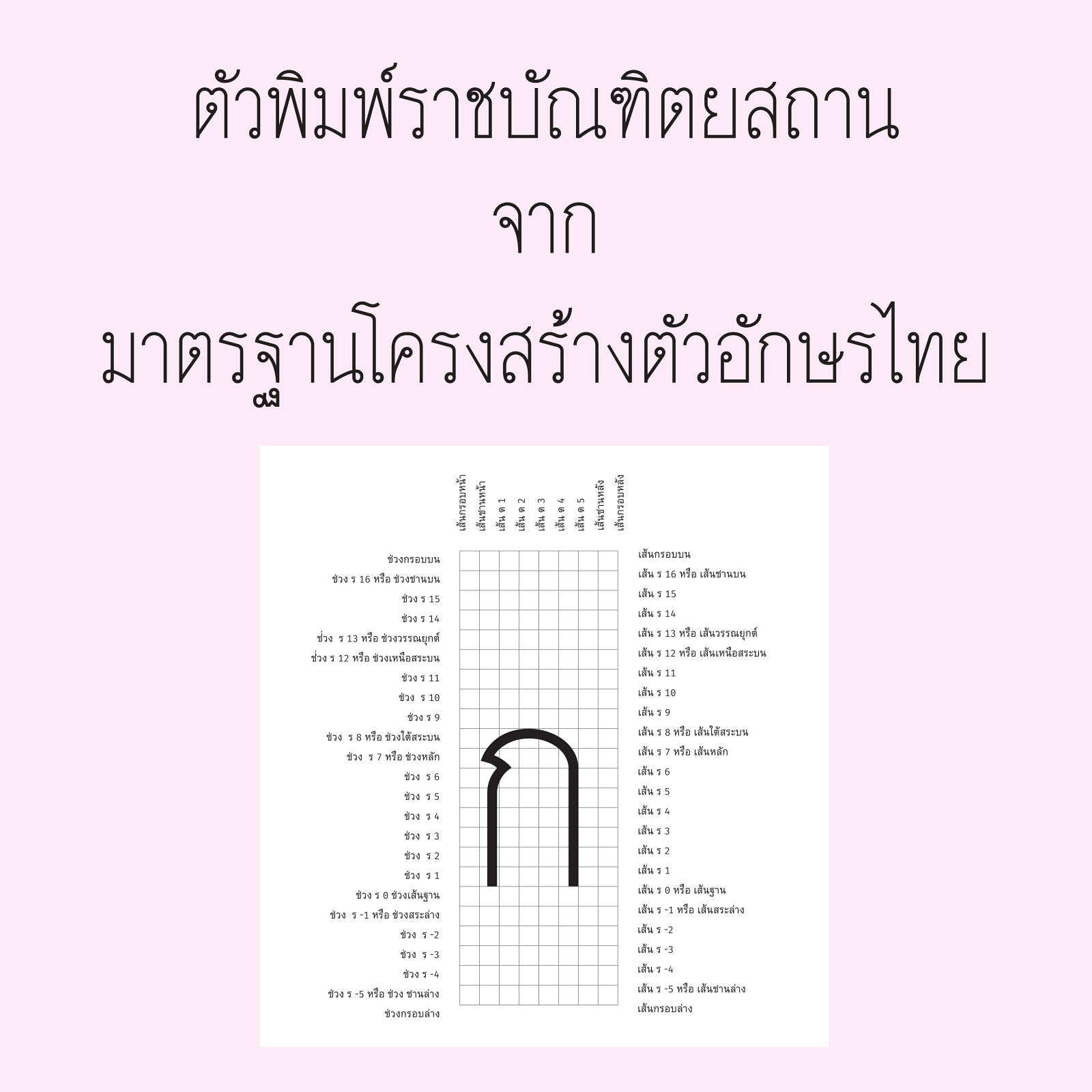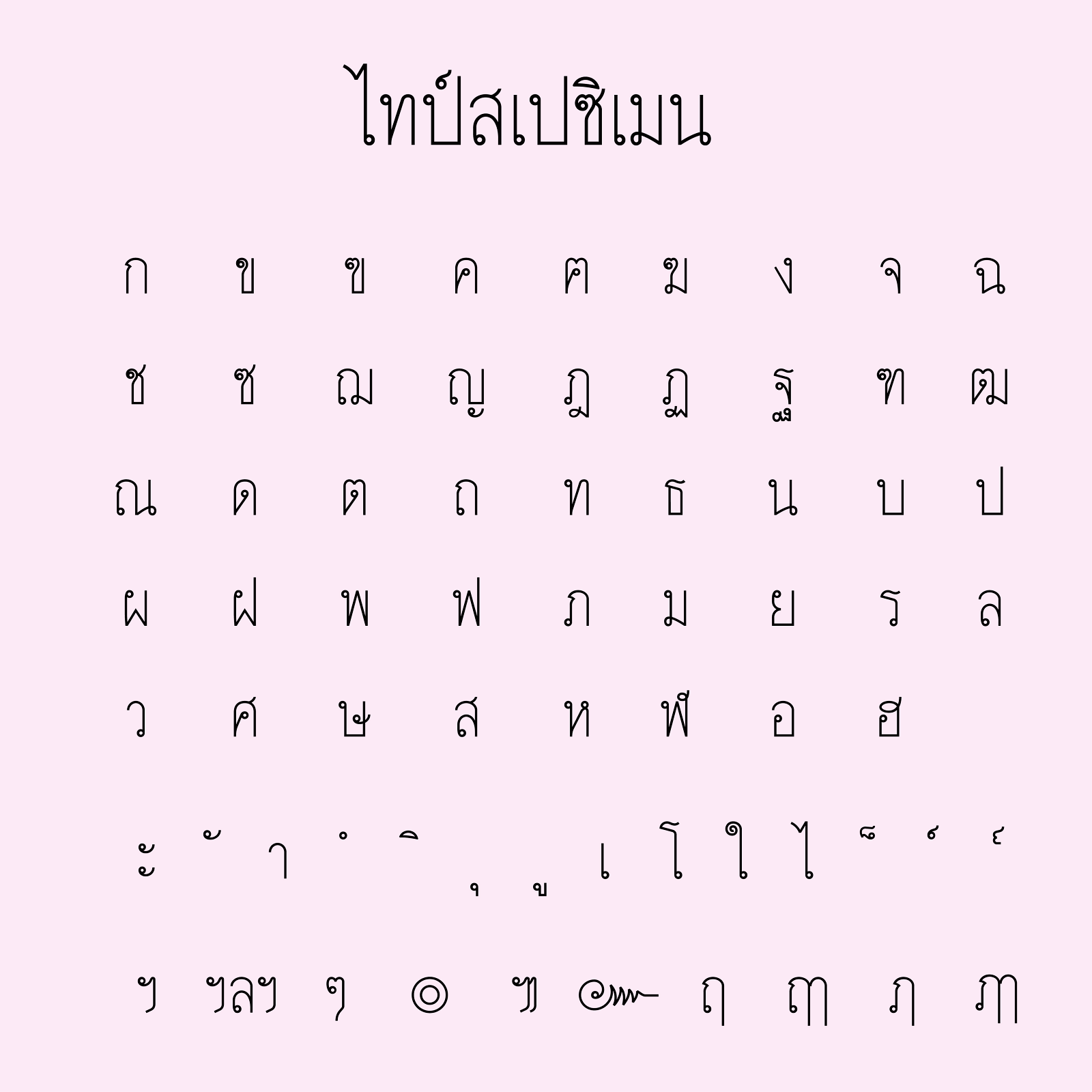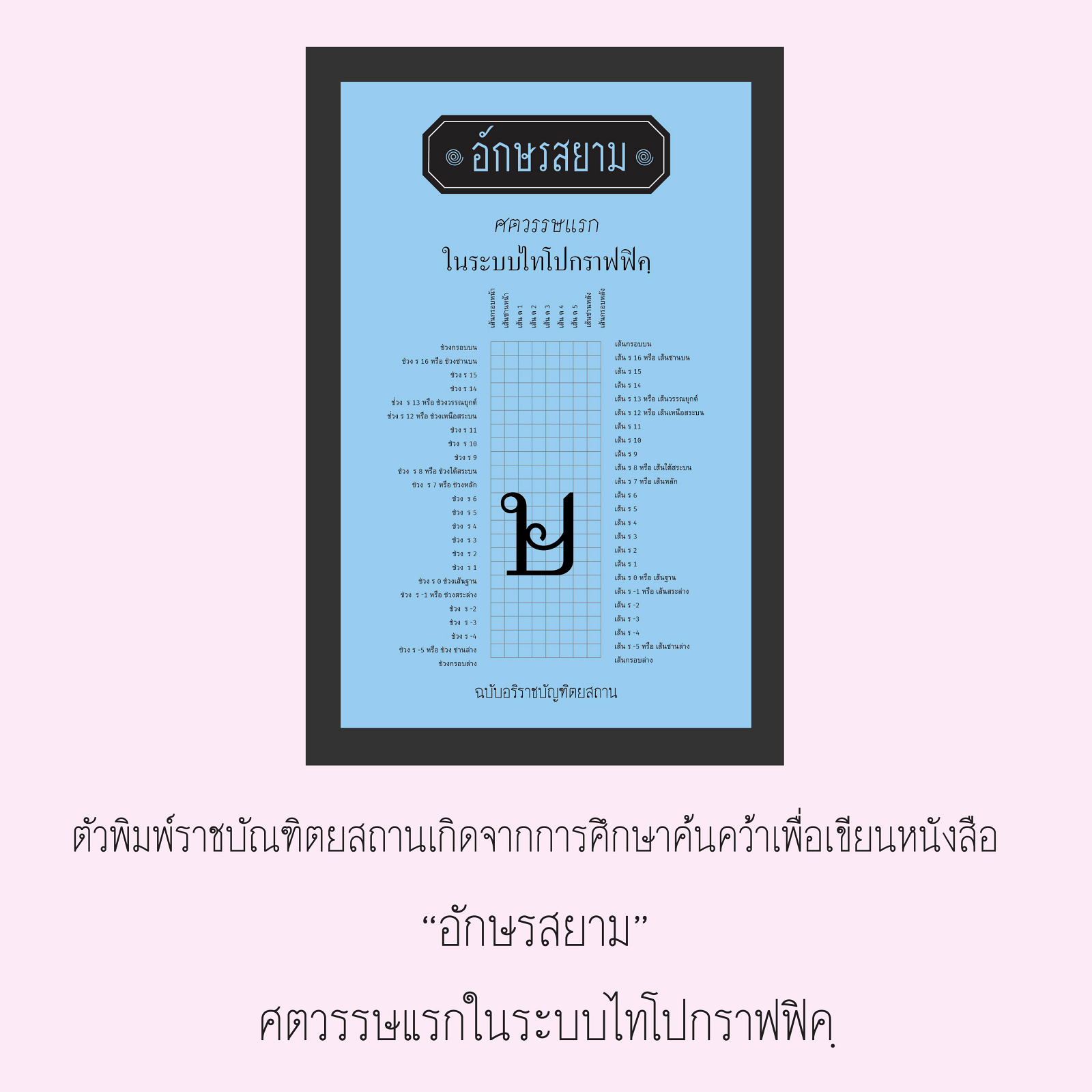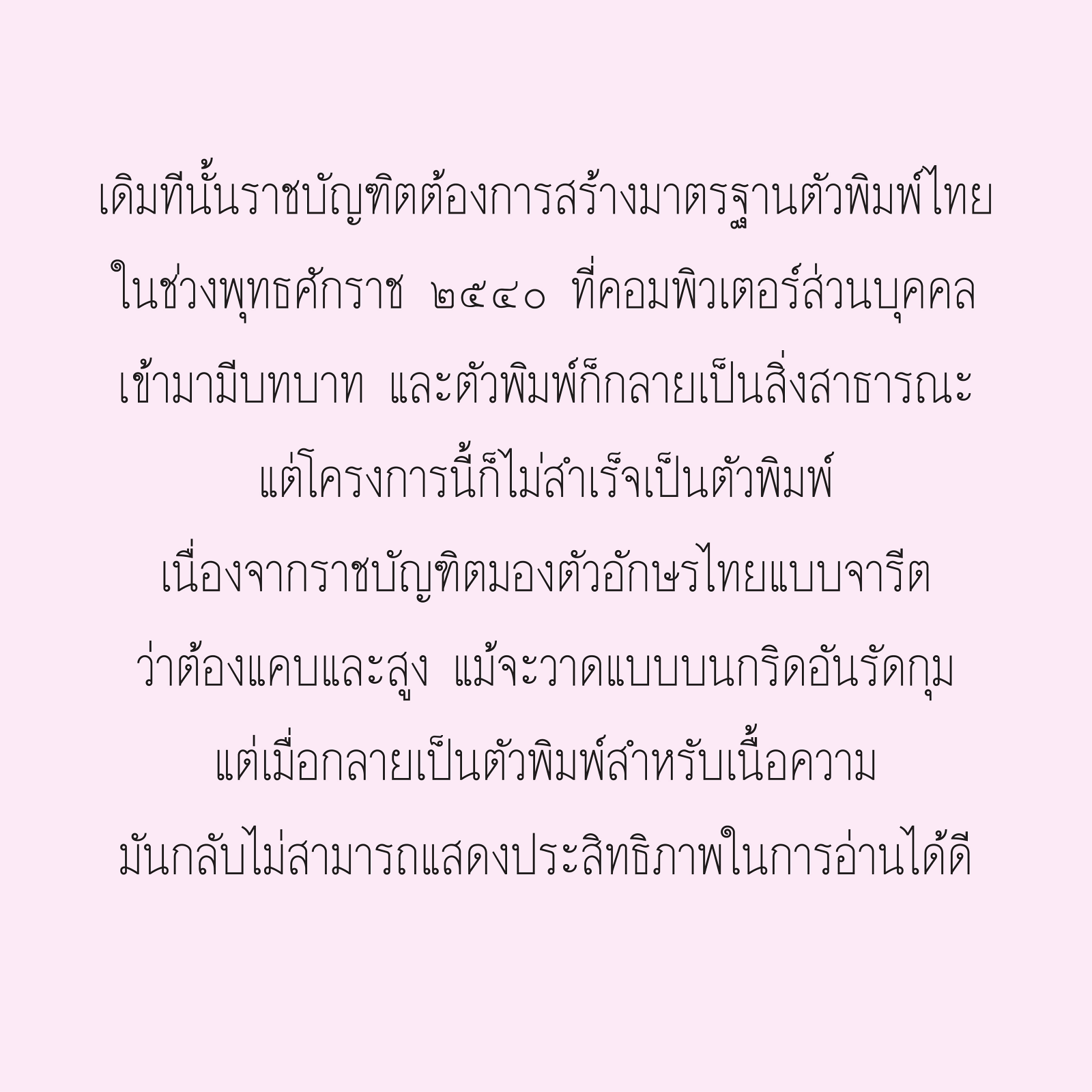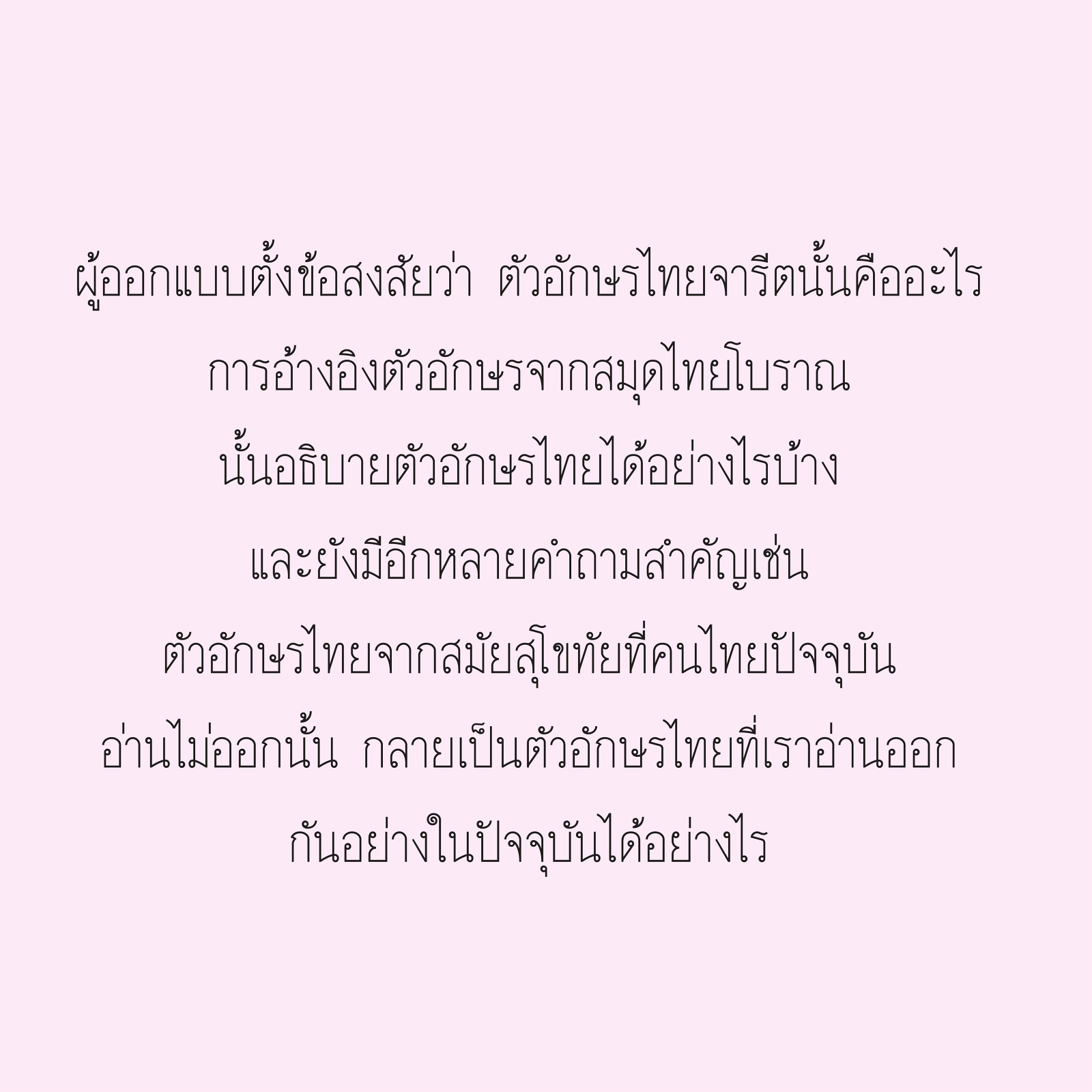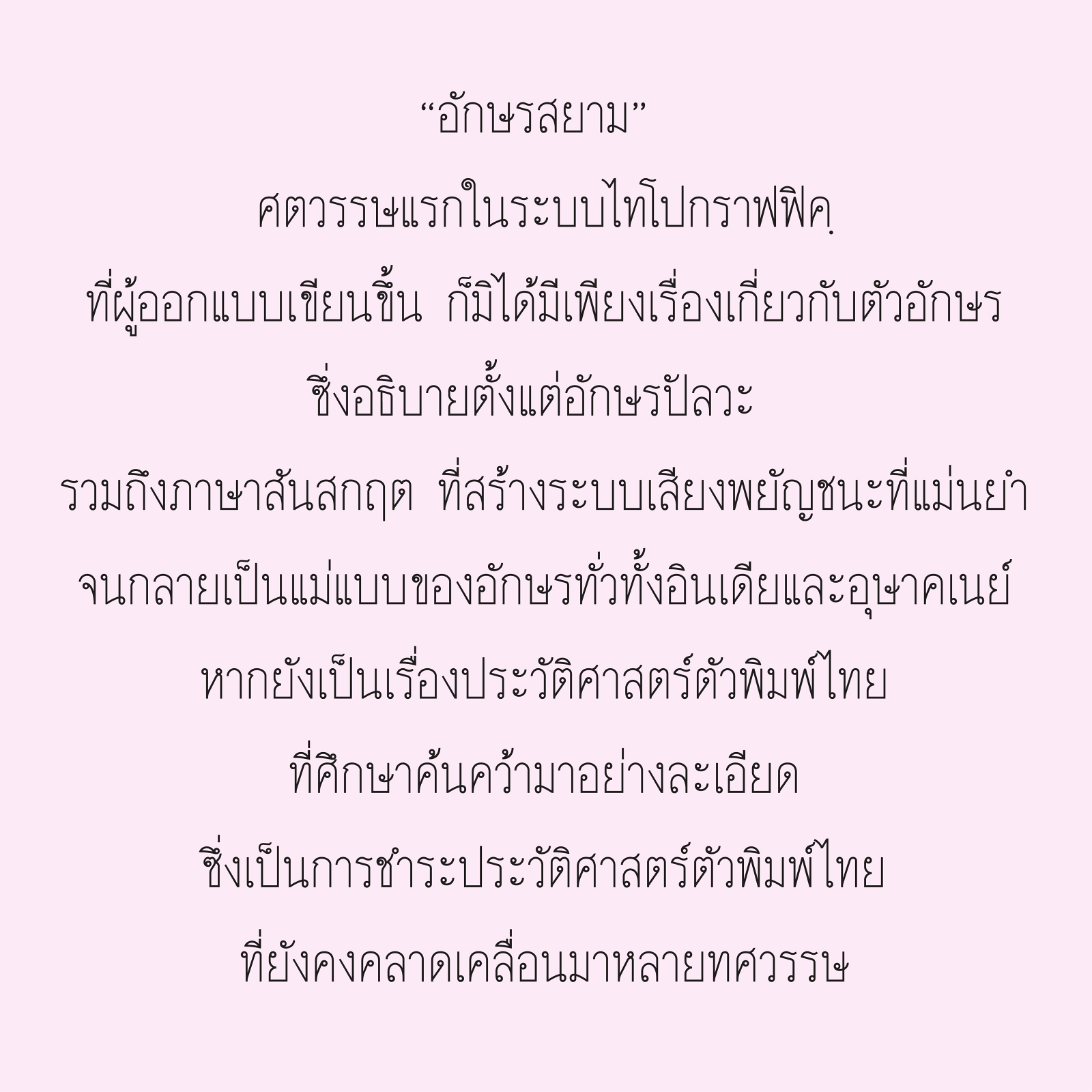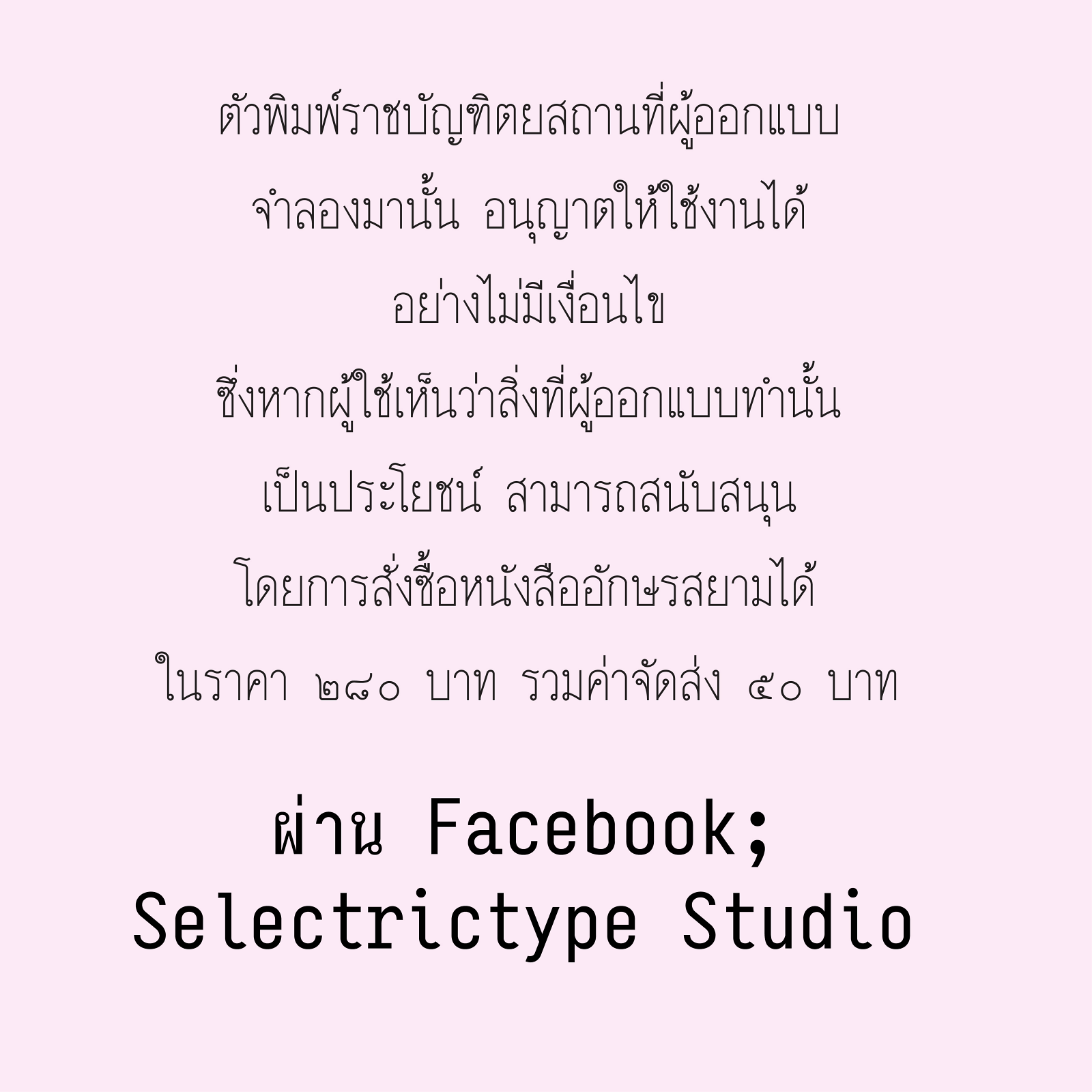
ราชบัณฑิตยสถาน (Royal Institute of Siam New)
ฟอนต์นี้เผยแพร่ให้ใช้เป็นประโยชน์ทางสาธารณะโดยไม่มีค่าใช้จ่ายแต่อย่างใด ซึ่งการจำลองแบบตัวพิมพ์ราชบัณฑิตยสถาน จากมาตรฐานโครงสร้างตัวอักษรไทยนี้ เป็นส่วนหนึ่งในการค้นคว้าศึกษาเพื่อเขียนหนังสือ “อักษรสยาม ศตวรรษแรกในระบบไทโปกราฟฟิคฺ